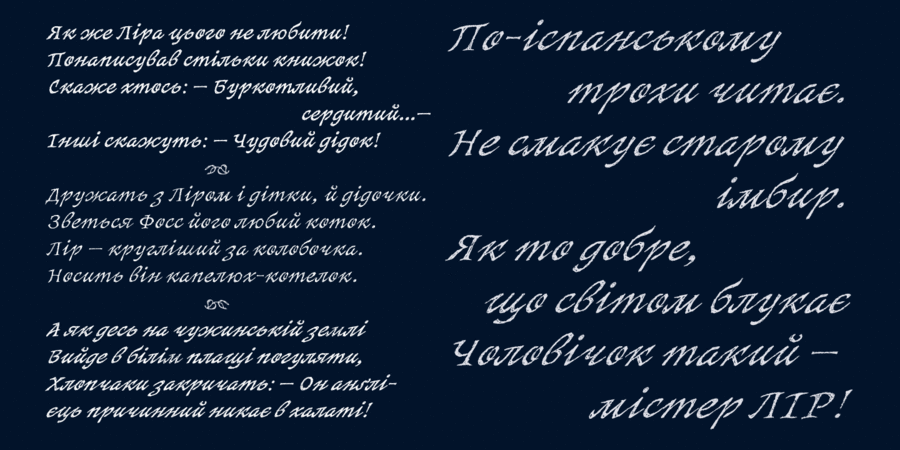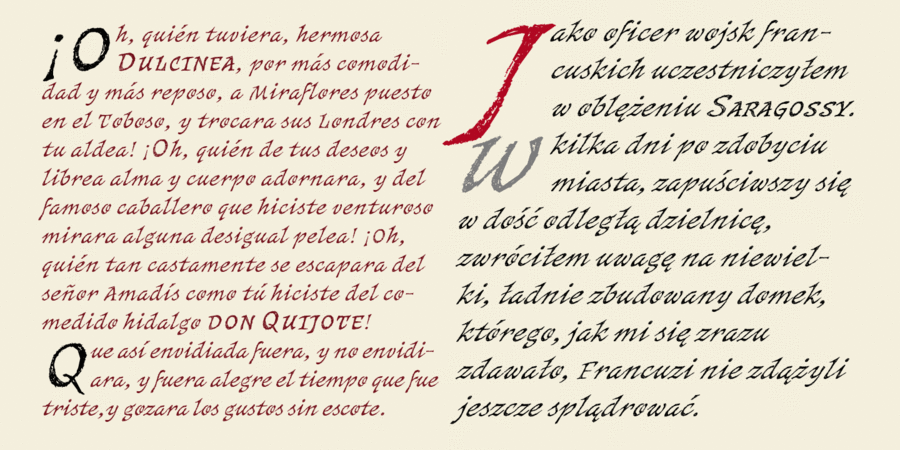
Значення неформального курсиву для культури взагалі та становлення шрифту зокрема вочевидь недооцінено. Більшість текстів було написано саме курсивами – від офіційних документів та світової літератури до найприватніших листів. Приблизно з 15 століття, здебільшого в Італії, розвивався «навколоантиквений» «гуманістичний» курсив – канчеляреска. На межі 15 та 16 століть Франческо Ґріффо створив, а Альд Мануций належно оцінив та вжив перший друкований курсив. Його використання дозволило Дому Альда випустити перші зручні малоформатні, відносно дешеві серійні видання абсолютно пізнаваного вигляду (що зумовило його пізнішу назву – «італік»). Цей курсив став настільки привабливим, що через права на нього судилися та здобували ексклюзивні привілеї, що лише прискорило його «піратське» розповсюдження. Шрифт SketchItalic – це дещо наївне й іронічне узагальнене уявлення про «ідеальний курсив», навмисно виконане у пошарпаній ескізній манері. Це робить його жвавим і неформальним та дозволяє імітувати друк чи письмо на цупкому папері. У великих кеглях шрифт виразно акцидентний з присмаком рукотворності, у малих – достатньо добре читається не втрачаючи неформального настрою. Добре поєднується з малюнками та нагадує шкільне письмо, що робить його доречним для оформлення дитячих книжок. SketchItalic підтримує європейську латинку та сучасну слов’янську кирилицю. Містить орнаментальні узгоджені між собою флерони. Чотири стандартні накреслення розширюють діапазон використання – вар’ювання розмірів, виділення в тексті, імітація різних почерків тощо. Шрифт розробив Віктор Харик у 2019 році.
Асоціації з сімейством шрифтів SketchItalicОсобистість і характер гарнітури:
гострий, історичний, ролевий, середньовічний, старовинний, казковий, артистичний, химерний, цікавий, оригінальний, традиційний, чарівний, майстерний, художній, естетичний, антикварний, королівський, пивний, колючий, різкий, грубий, емоційний, характерний, виразний, дивний, дикий, живий, ремісничий, кустарний, крафтовий, древній, рослинний, лісовий, кріповий, осінній, артізанальний, старомодний, самобутній, динамічний, колоритний, рукотворний, натуральний, творчий, чаклунський, магічний, архаїчний, вільний, етнічний, природний, активний, органічний, племінний, ритмічний, швидкий, грунтовий, нервовий, стрімкий, біжить, швидкісний, квапливий, зухвалий, темпераментний, мотивуючий, дерев'яний
пиво, ресторан, пивна, алкоголь, казка, історія, лицар, реконструкція, гра, театр, татуювання, тату, сувенір, магія, чарівник, Чарівна казка, кафе, меню, король, карти, антикваріат, таверна, вино, обід, вечеря, замок, сир, музика, монстр, ремесло, геловін, осінь, Самайн, сувій, дракон, фентезі, кузня, чаклун, тварюки, закляття, спеції, манускрипт, гравюра, м'ясо, література, фольклор, танець, літопис, природа, банкнота, перець, пригоди, дитяча книжка, туризм, легенда, комп'ютерна гра, графіка, ілюстрація, пейзаж, шолом Гарнітура має ознаки стилів: